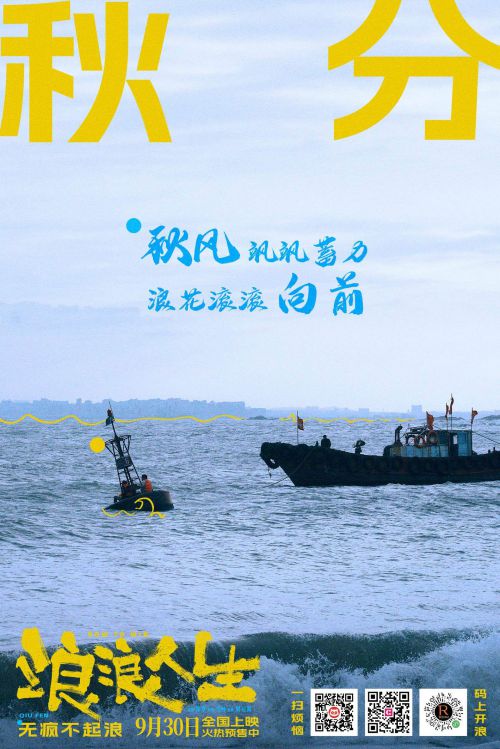
阿里妈妈数黑体
阿里妈妈数黑体是一款兼具趣味性与简约风格的创意字体,支持简体中文常规字符集,字重设置为正常,提供免费商用授权。字体整体呈现方正结构,重心居中且中宫适中,带来稳定平衡的视觉感受。其以独特的直角笔型为设计亮点,搭配粗壮且均匀的笔画线条,方头笔画的处理强化了字体的硬朗质感与醒目的视觉张力。巧妙的笔画断开设计打破了封闭感,增添了字体的灵动感与呼吸感,使简约风格中透出活泼趣味。阿里妈妈数黑体适用于标题设计、广告宣传、社交媒体配图等多种场景,既能通过厚重笔画突出信息层级,又能凭借创意细节提升视觉记忆点。作为一款免费商用字体,它完美融合了实用性与设计感,是追求个性表达与商业应用的理想选择。